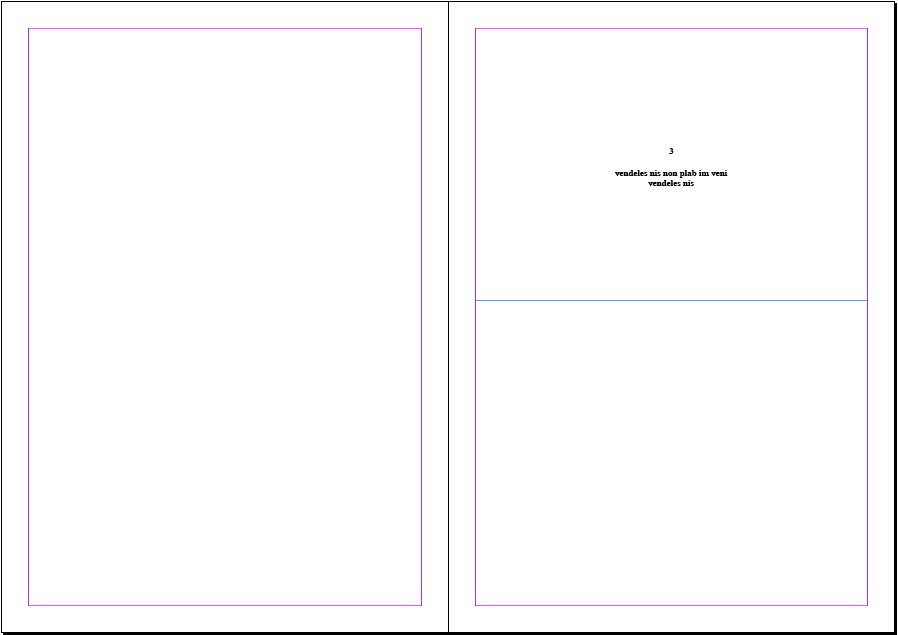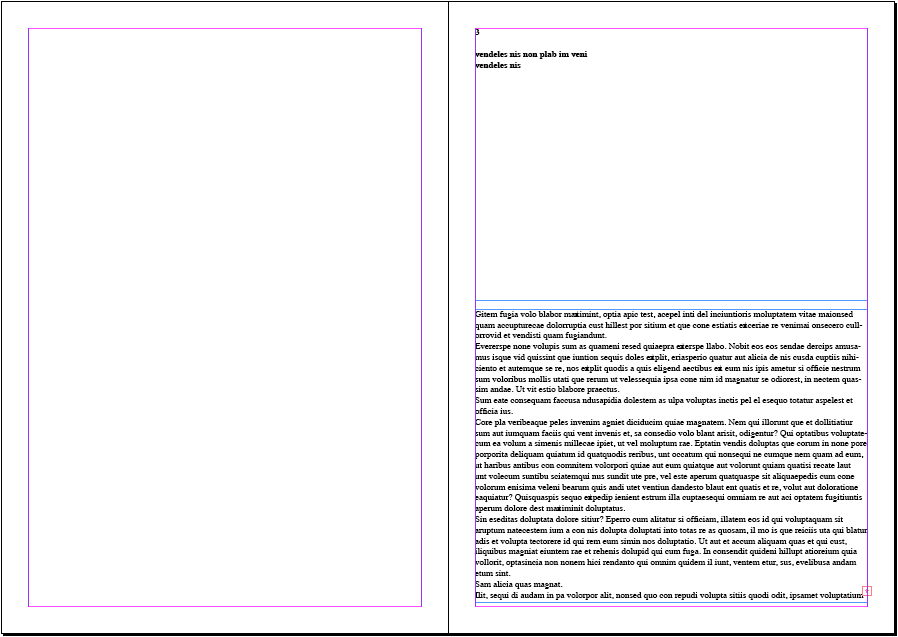
Schrift-Kombi für Projektarbeit im Bereich der Geschichtswissenschaften
Das ist eine wirklich gute Wahl! Jetzt kannst Du Dich entspannt zurücklehnen, durchatmen und dann Deine Arbeit in eine dem Thema angemessene und lesefreundliche Form bringen. Ich wünsche Dir Freude und Erfolg damit!
Der Satz selber ist fast wichtiger als die Details in einer Schrift, die in Lesegröße keiner bemerkt ;-)
Ich darf doch nochmal zitieren :)
Jetzt noch den Blocksatz optimieren (nicht zu stark schwankende Wort-Zwischenräume, trennen darf man um das zu erreichen) und das Minus durch einen Gedankenstrich ersetzen.
Finde auch den Zeilenabstand noch etwas groß. (weiß nicht wie es den anderen hier geht)
Bin kein Freund von zu engen Zeilen, aber bisschen weniger darfs schon sein – oder gibts ne Vorgabe ?
Wovon redest du, gibt es hier schon ein Satzentwurf, den ich ich nicht sehe?
das Vergleichs-pdf
wenn ich Schriften vergleiche schau ich schon, dass ich schonmal versuche bisschen zu optimieren.
Für eine Beurteilung stören mich Lücken und falsche Zeichen ziemlich.
Es geht um das PDF, in dem Schnecko die Schriften verglichen hat. Aber die Fehler müssen in dem Zusammenhang nichts bedeuten.
Den Blocksatz optimiere ich natürlich im Text ;) bei Überschriften habe ich den linksbündigen Flattersatz.
Vorgabe ist ein Zeilenabstand von 1,5 bei Schriftgröße 12.
Totaler Schwachsinn, da Abstand ist zu groß.
Ich denke das Internet bietet da auch genügend Möglichkeiten :) die Feinheiten kann ich später noch ausarbeiten!
Ich dachte mir das folgendermaßen:
Abschnittsüberschriften (1.1) mit Baskerville 10 Pro Bold in Schriftgröße 12
Fließtext mit Baskerville Pro 10 in Schriftgröße 12
Aber welche Schrift (in welcher Größe) für die Kapitelüberschriften (1.)  ?
Etwas ohne Serifen? (Hypatia?)
eine Empfehlung zum Schriftmischen bekommst du von mir nicht
du kannst auch durch die Position der Überschrift die Kapitel auszeichnen, musst dabei weder Schriftgrad noch Schriftart ändern.
z.B. Überschrift oben, den Text dann erst auf mittlerer Höhe beginnen lassen
oder der Kapitelüberschrift eine ganze (rechte) Seite einräumen ...
es kommt da halt generell auch auf deine Gleiderung an – wie viele Kapitel gibt es ?
Würde da auch die Bold in 12pt nehmen